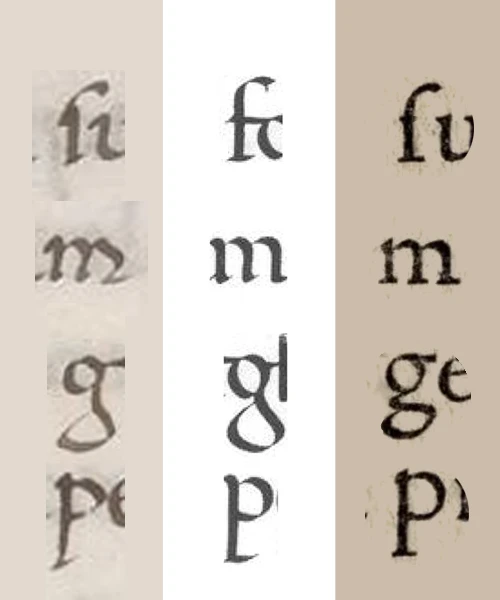
Siempre que nos referimos al nacimiento de la imprenta, debemos hacer la salvedad de que las primeras formas de tipográficas no heredaron los modelos de escritura humanística, sino las formas góticas.
En este artículo, nos enfocaremos en el origen de algunos diseños nacidos en el renacimiento y de sus reinterpretaciones posteriores.
Escrito vs. impreso
Es evidente que los modelos manuscritos formaron la base para los tipos móviles. La diferencia fundamental entre ambas técnicas es que en la imprenta los caracteres deben desarrollar sus formas dentro de espacios rectangulares. En ese sentido, la Textur manuscrita -que fuera la forma adoptada por los primeros impresores alemanes, se caracterizaba por una implacable regularidad en los trazos y consecuentemente muy apta para las restricciones que presentaba la técnica de la imprenta: la modularidad. Frank E. Blokland ha hipotetizado que esta regularidad de trazos facilitó la translación de los caracteres manuscritos a un sistema altamente estandarizado como es la imprenta. Por el contrario, en el caso de la escritura humanista, el menor ritmo modular obligó a una mayor libertad por parte de los punzonistas. Consecuentemente, en los primeros tipos romanos, la influencia de los modelos manuscritos es más bien morfológica, mientras que los detalles y las proporciones finales están más bien ligadas a exigencias del proceso de estandarización.
Escritura y tipografía: una relación circular
Recordemos que la invención de los tipos móviles no dejó obsoletos los libros escritos a mano. Durante un tiempo considerable, coexistieron ambos y los tipos móviles influenciaron las formas de la escritura. Así un gran número de manuscritos realizados durante finales del siglo XIV se copiaron de los primeros libros impresos porque, por entonces, ya circulaban muchos de ellos.
El fundational de Edward Johnston, tiene su origen en modelos tardíos de la Edad Media y se utilizó (y se sigue utilizando) en la educación de diseñadores para vincular la letra romana directamente con la escritura humanística. Sin embargo, este modelo también es una interpretación de modelos históricos que fueron definidos mucho después de la invención de los tipos móviles. Por eso es imposible desconocer las influencias recíprocas entre escritura y tipografía. Para ilustrar esta lógica circular, podemos comparar las imágenes ampliadas de una de distintas minúsculas. Las de la izquierda pertenecen a la escritura de Gian Francesco Poggio Bracciolini (1380-1459), comúnmente conocido como Poggio, a quien se le atribuye la minúscula humanística, las del centro corresponden al modelo la fundational y las de la derecha a la del tipo romano de Jenson. Aunque los signos comparten la misma estructura, hay una gran diferencia entre las letra de Poggio y el tipo de Jenson. Hay similitudes de estructura, que Jenson estandarizó rígidamente. A su vez, los modelos caligráficos de escritura humanística fue indudablemente influenciados por esta estandarización de la imprenta. La teoría generalmente aceptada es que Jenson y sus colaboradores intentaron imitar la escritura a mano, pero esa opinión se contradice cuando vemos como el modelo de Poggio difiere claramente del de Jenson. Jenson ideó un modelo relacionado con la escritura, pero al mismo tiempo diferente estableciendo un nuevo estándar.
Comparando ambas técnicas
Comparar la caligrafía con la producción tipográfica implica tomar en consideración la inherente diferencia entre los dos procesos. La estructura de los tipos móviles es bastante simple: las letras se colocan en rectángulos, lo que produce que, independientemente de la secuencia de letras, el patrón rítmico da como resultado el mejor equilibrio posible de espacio en blanco. La repetición de formas de letras reproducidas con precisión y una distribución estandarizada del espacio son aspectos característicos de la tipografía. Incluso cuando se poseen diferentes glifos de ciertos caracteres en una fuente (lo que se hace para aproximarse a la versatilidad de la escritura a mano), dará como resultado un un grado de repetitividad, debido a lo finito de las variantes. Los caracteres escritos, por el contrario, nunca son completamente idénticos y siempre se ajustarán hasta cierto punto a su contexto. Hay otra diferencia importante entre ambas: en la escritura hay patrones rítmicos de formas en blanco y negro y si es necesario, pueden adaptarse las formas de las letras, haciéndolas más condensadas o más expandidas, para ajustar el patrón, por ejemplo, a la longitud de una línea. El diseñador tipográfico tiene que dividir el espacio entre las letras por igual para crear un gris parejo. La flexibilidad y libertad que tiene el calígrafo a la hora de controlar el espacio dentro y alrededor de las letras tiene que ser aproximado en tipografía y se hace agregando ligaduras, alternativas contextuales y correcciones en el espaciado para combinaciones de letras específicas. Otra diferencia entre la tipografía y la escritura es que en esta última no hay límites verticales estrictos entre líneas. Las longitudes de los ascendentes y los descendentes pueden variar, incluso cuando la distancia entre las líneas se mantenga constante.
En los manuscritos humanistas la altura x es el factor más constante; las longitudes de las ascendentes y descendentes mucho menos. En tipos móviles, los límites verticales están tan estrictamente definidos como los horizontales. Esto da como resultado proporciones verticales fijas para los rectángulos en donde se desarrolla la forma de cada letra más el espacio circundante. La estructuración del tipo móvil, que está destinado a la reutilización de letras, es completamente artificial. Walter J. Ong, hace una interesante distinción entre escritura y tipografía declarando que, en el caso de la escritura, las palabras se forman creando marcas en las superficies mientras que con tipografía se hace «a partir de cosas preexistentes.» Esta definición está relacionada con la descripción que Noordzij hace de la tipografía como «escritura con letras prefabricadas», que enfatiza el concepto de que escritura y tipografía son cosas básicamente diferentes.
Tipografía y humanismo
El humanismo renacentista como movimiento intelectual, filosófico y cultural europeo cuyo origen se sitúa en la Italia del siglo XV, especialmente en Florencia, Roma y Venecia va dirigir su atención hacia la antigüedad clásica que significaba no sólo la recuperación de las obras griegas y romanas, sino fundamentalmente al intento de retornar al principio de la vida cultural del ser humano. Para cuando dos clérigos alemanes llamados Konrad Schweynheim y Arnold Pannartz, llegaron al monasterio de Subiaco, en la tranquila reclusión de las colinas sabinas al este de Roma, la escritura humanista había evolucionado por completo y ya era una opción natural para los libros manuscritos de literatura clásica.
Si bien la imprenta se había extendido desde Mainz a mediados de la década de 1450 a otras ciudades de Alemania, pasaría una década antes que atravesara los Alpes. Y no lo haría ni en la cosmopolita Venecia ni en Roma, sino en un tranquilo monasterio benedictino en Subiaco. Hacia 1464, Sweynheym y Pannartz se establecieron allí y comenzaron imprimiendo 300 copias de una gramática de Elio Donato, de la que, lamentablemente, no se ha conservado ninguna copia. Su siguiente edición, publicada hacia 1465, fue De oratore de Cicerón. Se lo considera el primer libro impreso y fechado en Italia y así comienza la asociación de la imprenta con las obras de los clásicos.
Sweynheym y Pannartz modelaron las formas de sus tipos basándose en manuscritos italianos. Claro que no existía un modelo único, como tampoco existía una escritura humanista única. Si analizamos las mayúsculas del tipo Subiaco, vemos que son claramente romanas, aunque existe, y era de esperar en un primer esfuerzo, una falta de unidad entre mayúsculas y minúsculas. Por ejemplo, la tensión o el eje en las mayúsculas es a veces casi perpendicular, mientras que en las minúsculas es oblicuo. Asimismo, el tratamiento del serif es bastante fortuito. Presenta muchas concesiones a la escritura como las variaciones en sus caracteres y el resultado del texto es de un color relativamente oscuro.
El hecho de que no hubiera un mercado local para sus libros probablemente precipitó su mudanza a Roma en 1467. Sweynheym y Pannartz con su imprenta romana recién establecida, produjeron un nuevo tipo romano. Este segundo romano presenta un enfoque de los serifs es bastante más consistente. Algunas de las mayúsculas son más anchas: en particular la “E”, “F” y “K”. En minúsculas, la mayoría de las letras son más anchas, incluida la “e”, que tienela barra transversal extendida. Además, los cuencos son más redondos: estas características hacen que el color de esta segunda romana sea más clara. Sweynheym y Pannartz pasaron a la historia por haber introducido el libro tipográfico y la tipografía romana en Italia, pero no fueron hombres muy emprendedores. En 1472 estaban al borde de la bancarrota, y su editor, Giovanni Andrea Bussi, solicitó ayuda al Papa.
Estas primeras versiones del tipo romano a la que podríamos agregar la de Ulrich Ham (otro impresor alemán establecido en Roma) según John Boardly podrían denominarse como proto-romanos y estaríamos incluyendo todos los tipos romanos producidos antes de Jenson (1465-1470). Ahora nuestro recorrido debe proseguir por Venecia, donde vamos a hablar del romano jensoniano (Nicolas Jenson) (1470-1495) y el romano aldino (Aldus Manutius, Francesco Griffo) (1495–) .
Pero lo que es interesante para nosotros es que Poggio también fue copista y transcribió muchos de los manuscritos que encontró de su propia puño y letra con caligrafía clara y elegante.
Con Poggio Bracciolini y Niccolò Niccoli, la escritura humanística nació alrededor de 1400 en Florencia. Poggio es considerado el padre de la escritura humanista en minúscula redonda (la llamada littera antiqua), Niccoli de la escritura humanista en minúscula cursiva.